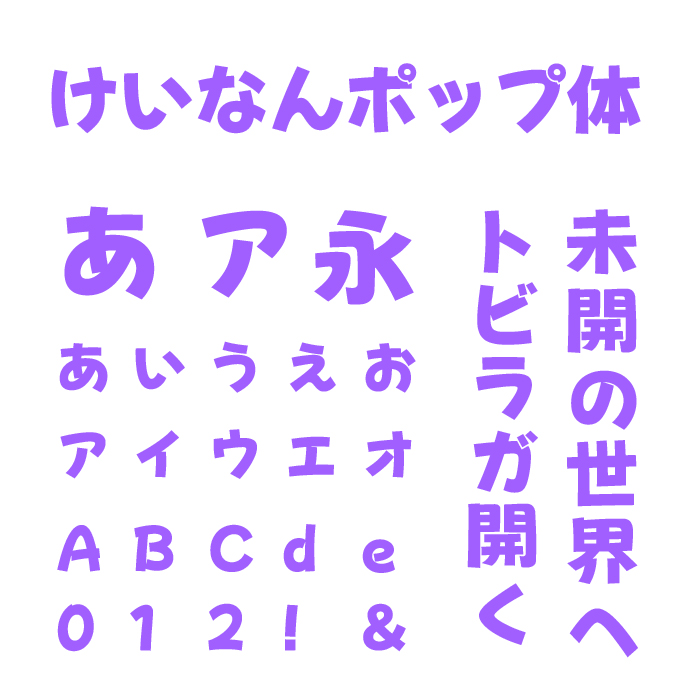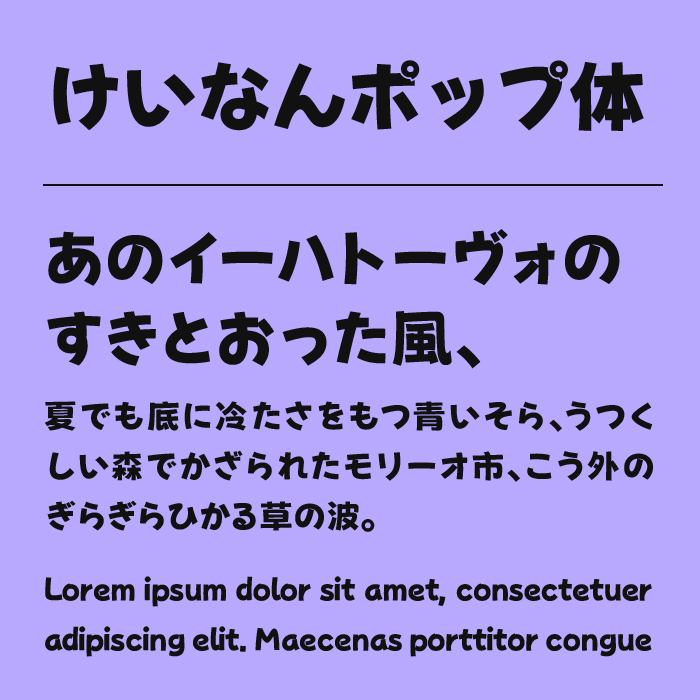
けいなんポップ体フォントは、柔らかなカーブと手描き感のあるフォルムが、親しみやすさと遊び心を感じさせるポップ体フォントです。
「源暎ぽっぷる」フォントと「荆南波波黑」フォントを組み合わせて作られた合成フォントです。ひらがな・カタカナ・英数字がすべて丸みを帯びており、どの文字も統一感を保ちながら表情豊か。POPや教育向け、キッズコンテンツなど、やさしく包み込むようなトーンにぴったりのフォントです。